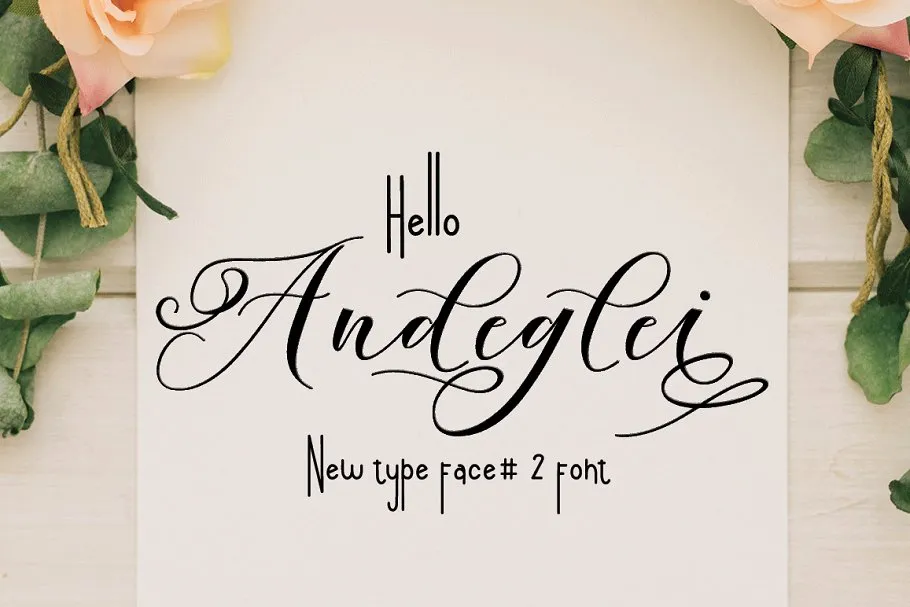
Andeglei Font Duo é uma elegante fonte sans-serif com estilos manuscritos monolineares que oferece um toque sofisticado e moderno aos projetos digitais. Esta fonte caracterizada por sua linhas robustas, dinâmicas e perfeitamente combinadas com os estilos monolineários, cria um visual atraente para diversos usos, como logotipos, cartões de visita, convites de casamento, subtítulos, assinaturas, camisetas, folhetos de apresentação, etiquetas, outdoors e até mesmo gráficos. Seu design contemporâneo e seu uso versátil a tornam uma opção ideal para designers buscando incorporar um toque sofisticado em suas criações. Engane-se se pensa que é apenas uma fonte sans-serif, Andeglei Font Duo traz ao seu projeto um toque de elegância moderna que certamente deixará seus projetos brilharem ainda mais.